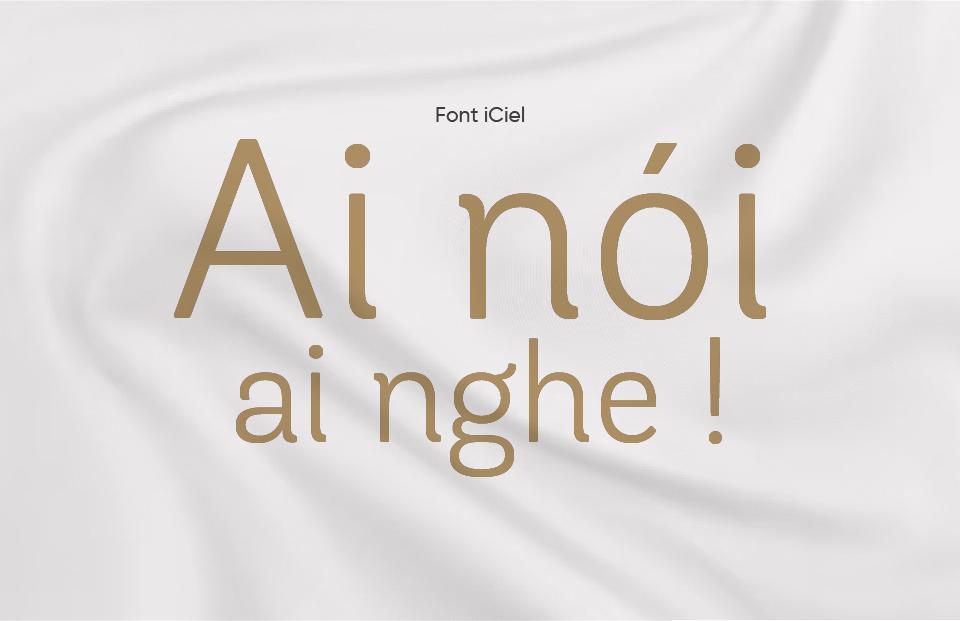
Font iCiel Andes Rounded Light là một phiên bản nhẹ nhàng và tinh tế trong bộ sưu tập font Andes, nổi tiếng với thiết kế độc đáo và linh hoạt. Bản Rounded Light này mang lại sự mềm mại và thân thiện, với các đường nét bo tròn mượt mà, tạo ra một cảm giác ấm áp và gần gũi cho người đọc. Điều này làm cho font Andes Rounded Light trở thành sự lựa chọn lý tưởng cho các dự án thiết kế đòi hỏi sự nhẹ nhàng và không gian thân thiện, như thiết kế cho trẻ em, thương hiệu lối sống, và ứng dụng di động.
Được thiết kế để hỗ trợ đầy đủ các ký tự tiếng Việt, bao gồm cả dấu điệu và ký tự đặc biệt, Font Andes Rounded Light đảm bảo người dùng có thể thể hiện ý tưởng của mình một cách chính xác và rõ ràng. Sự chú trọng vào khả năng đọc và tính thẩm mỹ giúp font này trở thành lựa chọn lý tưởng cho cả văn bản và thiết kế đồ họa.
Font iCiel Andes Rounded Lightthích hợp cho việc sử dụng trong một loạt các ứng dụng thiết kế, từ branding, thiết kế logo, bao bì sản phẩm, cho đến thiết kế trang web và ấn phẩm quảng cáo. Sự nhẹ nhàng và mềm mại của Andes Rounded Light giúp nó trở thành lựa chọn hoàn hảo cho các dự án muốn truyền tải sự chuyên nghiệp, thân thiện và tiếp cận được với mọi lứa tuổi.
Ngoài ra, sự linh hoạt và dễ sử dụng của Font Andes Rounded Light cung cấp một nguồn cảm hứng lớn cho các nhà thiết kế và nghệ sĩ, cho phép họ thể hiện sự sáng tạo và tinh tế trong công việc của mình. Sự kết hợp giữa thiết kế tròn và nhẹ nhàng giúp tạo ra những tác phẩm độc đáo và nổi bật, góp phần nâng cao giá trị thẩm mỹ và sự thu hút của sản phẩm cuối cùng.